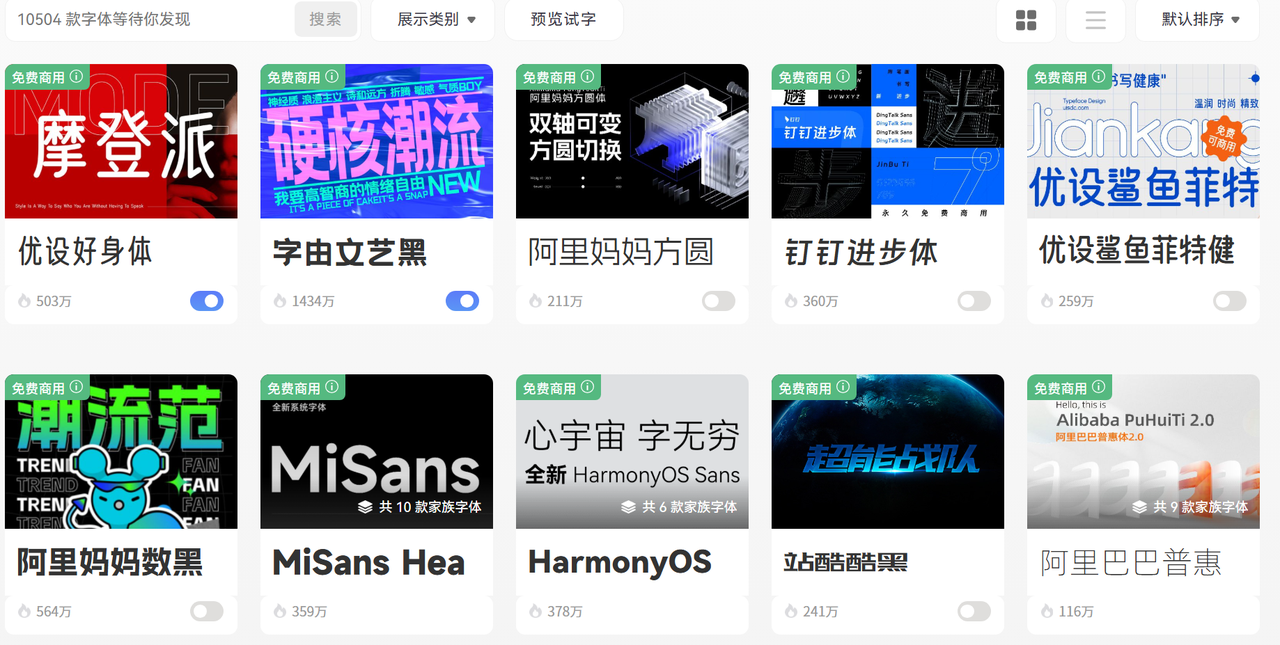
字体下载大全网站推荐,设计师必收藏的字体资源库
字体是设计的骨架,选错了整个作品气质全毁。字体资源的坑,说到底不是"找不到",而是"找不对"——免费的未必可商用,好看的未必支持中文,收费的又不知值不值。所以这篇文章想做的,不是给你甩一堆网址了事,而是把每个平台的真实定位说清楚:它适合谁用、能解决什么问题、有没有隐藏的版权坑。
一、字由网——字体下载大全"一站式管家"
如果只推荐一个中文字体平台,字由是绕不开的名字。字由目前收录上千款中英文字体,说起来可能没什么感觉,但它的分类体系才是真正体现诚意的地方。除了常规的风格分类(黑体、宋体、楷体、手写、书法……),字由还做了字体风格标签,比如:简约 / 现代/ 古典/中国风 / 手写风......选字的时候不用从头想"什么风格适合这个项目",直接按字体风格筛,出来的结果大多数时候已经在对的方向上了。对于接案子的设计师来说,这个功能在赶稿状态下能省下不少脑力。
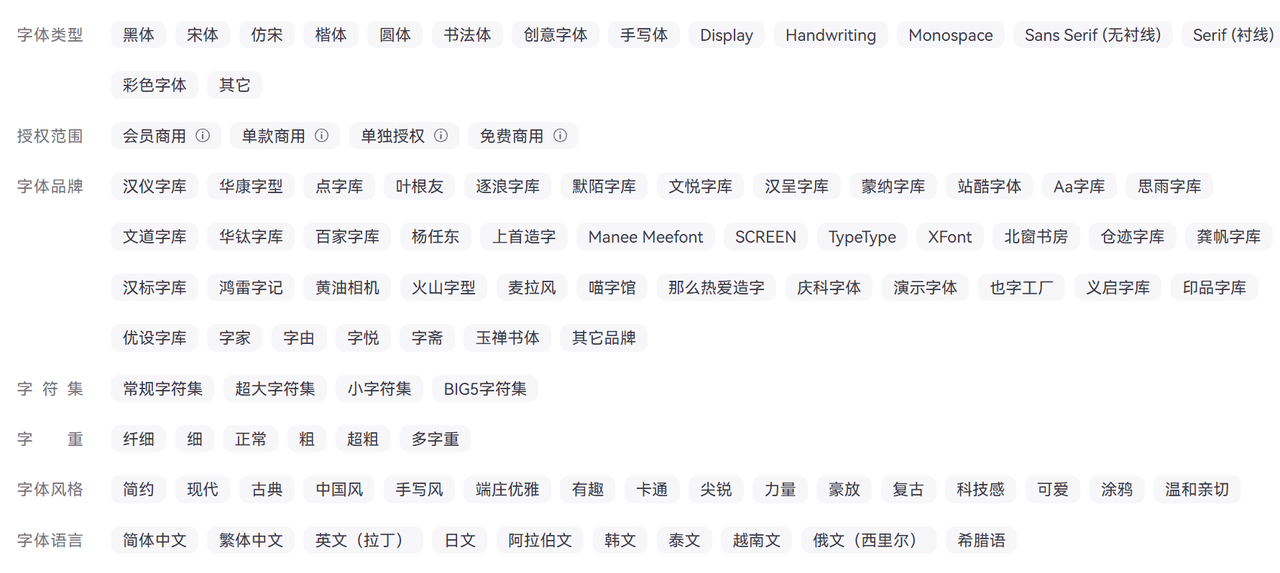
字库里也有不少独家或国内首发的字体,像站酷系列、锐字系列、方正部分字体都有收录,平时用到行业常见字体,基本不需要额外找来源。
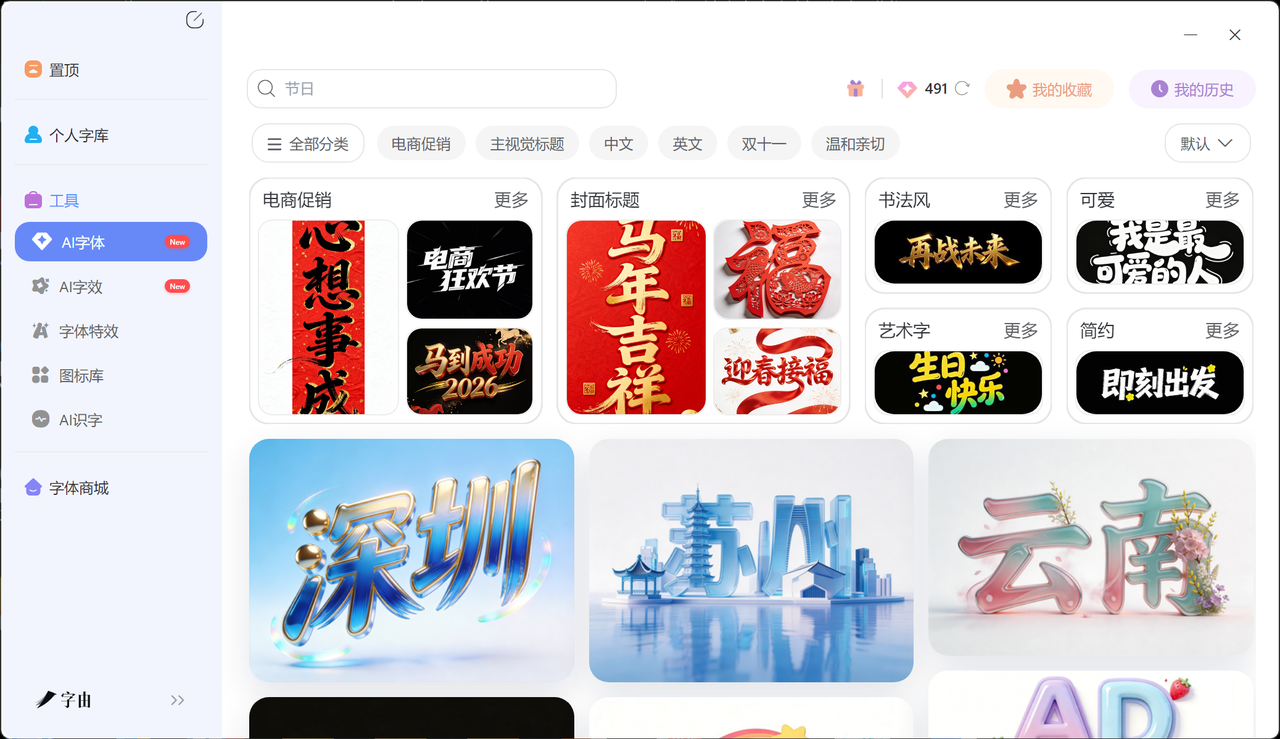
二、Google Fonts——英文字体的天花板免费库
做英文排版,Google Fonts 基本是行业默认选项。全库免费、全部开源、可商用,这三点放在一起,在字体行业已经算相当罕见。目前收录超过 1500 套字体族,从极简无衬线到复古衬线,从等宽代码字体到手写风格,覆盖面非常广。
一个小坑: 部分字体的中文支持不完整(或者根本不支持中文),做中英混排之前记得先测试一下,别等做完才发现中文全变成方块。
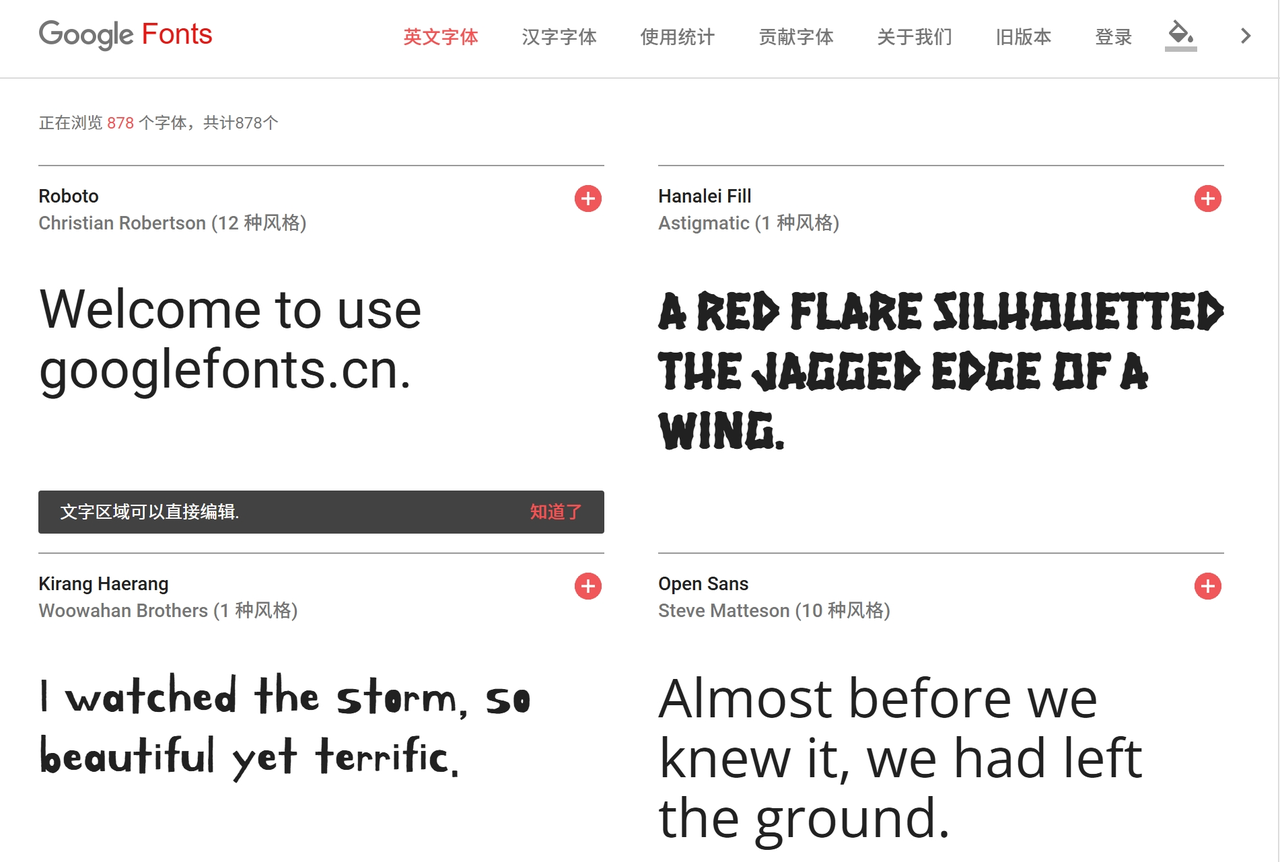
三、猫啃网——良心免费商用中文字体
猫啃网在国内设计圈口碑一直不错,原因很简单:它收录的字体都经过版权筛查,明确标注"免费商用",省去了设计师自己去查字体授权协议的麻烦。字体数量没有字由那么夸张,但胜在精,很多独立设计师发布的原创免费字体都会在这里首发或归档。如果你在找那种"别人用烂了的黑体之外"的差异化中文字体,猫啃是值得字体下载大全网站。
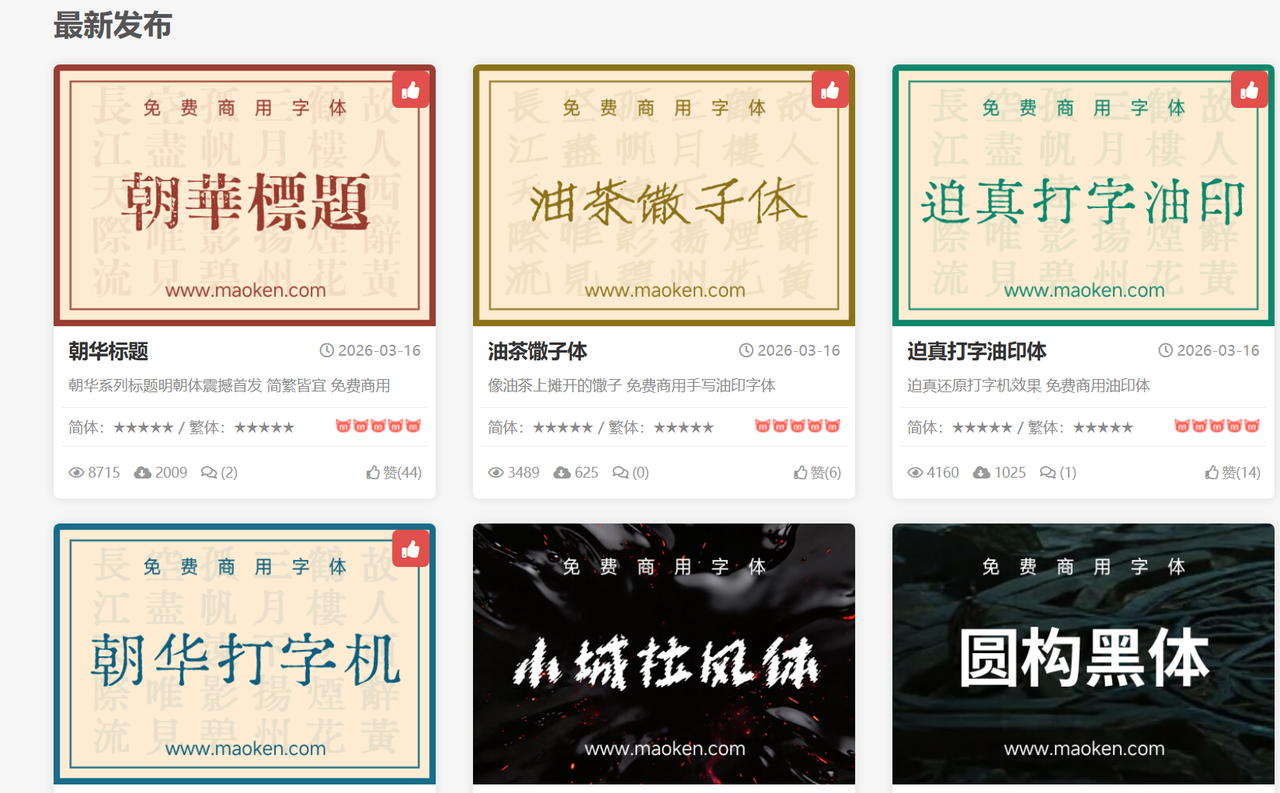
四、Adobe Fonts——CC 用户的隐藏福利
很多 Adobe CC 订阅用户没意识到自己已经有一个字体库白用。Adobe Fonts集成在 Creative Cloud 里,只要你订阅了 CC,就能访问 2 万款以上的字体,直接同步到 PS、AI、InDesign 等软件,不用手动下载安装。
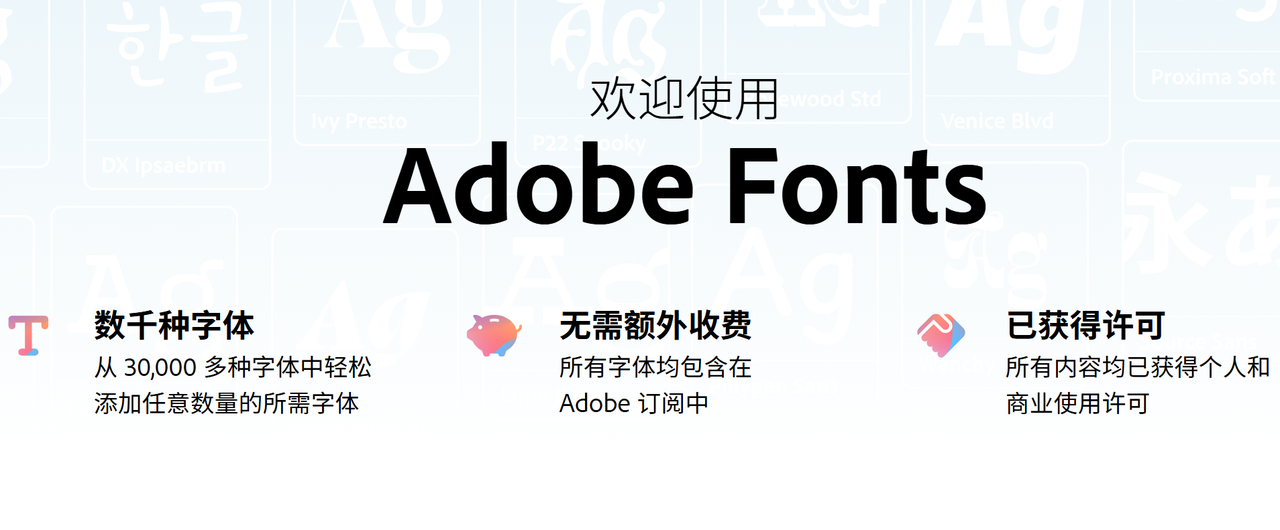
五、Dafont——个性英文字体的"杂货铺"
Dafont 是老牌英文字体聚合站,十几年前就已经是设计师常驻的地方。风格极其多样,像素字体、涂鸦字体、科幻字体、哥特体……每款字体的授权类型不同,页面上会标注"Free""Free for personal use""Shareware"等,商用之前一定要点进去确认授权协议,"Free"不代表可以商用。